Как подписать многоразовый контейнер для доставки: порядок возврата и контакт
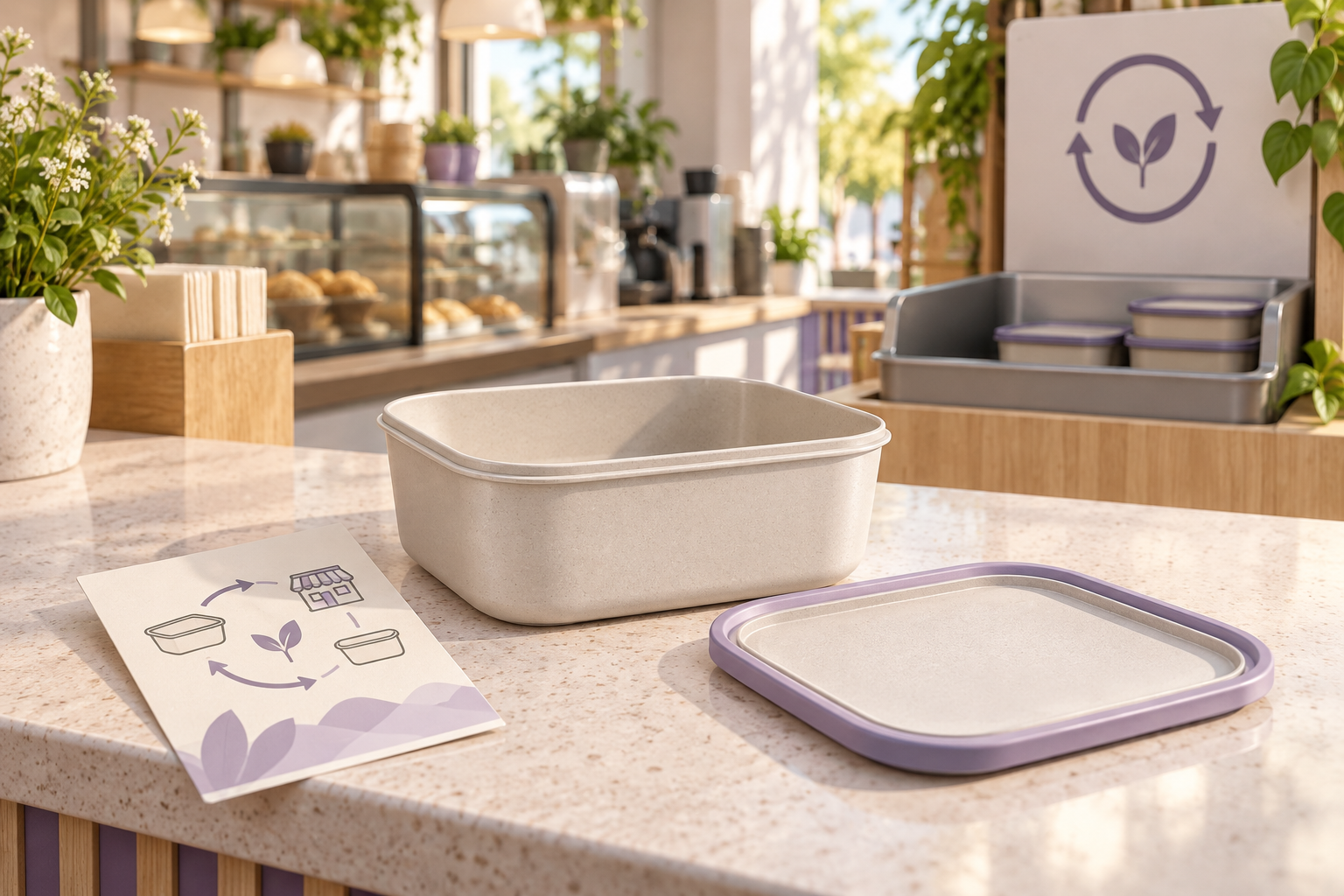
Многоразовый контейнер после доставки должен быстро ответить на три вопроса: нужно ли его возвращать, куда отнести и как связаться с кафе. Удобная инструкция видна до открытия упаковки, не теряется среди брендинга и остаётся понятной после еды. Ниже — способ собрать текст, расположить его на крышке или вкладыше и проверить макет в реальных условиях.
Сначала определите, что именно возвращает гость
Начните не с шрифта, а с предмета и сценария. У кафе может быть несколько видов тары: контейнер для горячего блюда, стакан, приборы или сумка. У каждого свой срок и маршрут возврата. Если написать только «верните упаковку», посетитель не поймёт, относится ли просьба к крышке, самому контейнеру или всему комплекту.
Составьте короткий перечень: какие предметы забирает гость, что из них возвращается и в каком состоянии. Обозначьте одно понятное название для каждого предмета и используйте его последовательно в сообщении, на заказе и у стойки. Если условия отличаются для разных позиций, не пытайтесь вместить несколько правил в одну универсальную фразу — сделайте отдельные наклейки или вкладыши.
Полезно заранее ответить на вопросы команды: принимают ли тару во всех точках или только в той, где выдали заказ; можно ли передать её курьеру при следующем заказе; куда положить грязный контейнер; как поступить, если точка закрыта. В печатной инструкции должны оказаться только варианты, которые заведение действительно готово выполнять. Не обещайте возврат через курьера или конкретный адрес, пока этот процесс не согласован внутри.
Постройте сообщение по порядку действий
Гость читает упаковку быстро: у двери, за столом или уже после еды. Поэтому инструкция должна работать как маршрут, а не как рекламный абзац. Сначала покажите действие, затем место, время или способ, а в конце — канал для вопроса. Если нужен депозит или другое условие, назовите его простыми словами и рядом объясните, где уточнить детали.
Для базовой карточки достаточно четырёх смысловых строк:
- Действие: «Верните контейнер» или «Контейнер можно вернуть».
- Место: точный адрес стойки, название точки или согласованный способ передачи.
- Срок или момент: только если он установлен и важен для работы сервиса.
- Контакт: короткий адрес страницы, телефон или QR-код с подписью о том, что откроется.
Используйте глагол, который описывает реальное действие. «Сдайте», «оставьте» и «принесите» звучат похоже, но задают разные ожидания: контейнер передают сотруднику, кладут в обозначенную зону или возвращают лично. Если тара принимается только чистой или пустой, сформулируйте это прямо и доброжелательно. Не прячьте такое условие в сноску.
Когда возврат добровольный, так и обозначьте его. Когда есть плата, залог или иной стимул, разделите шаг и условие: сначала что сделать, затем что произойдёт после. Избегайте формулировок «выгодно», «экологично» или «бесплатно», если рядом нет точного пояснения. Тон должен помогать гостю действовать, а не создавать ощущение упрёка.
Выберите поверхность: контейнер, крышка или вкладыш
Печатать всё на стенке контейнера удобно не всегда. Изогнутая поверхность деформирует строку, конденсат и жирные пальцы мешают чтению, а крышка может отделиться от основания. Сначала решите, в какой момент человек должен увидеть сообщение.
На крышке можно дать короткий первый сигнал: «Верните контейнер» и указатель на инструкцию. На боковой стенке — место возврата и контакт. Если поверхность мала, используйте отдельный вкладыш или бумажную ленту вокруг комплекта. Вкладыш позволяет разместить полную инструкцию, но его легко выбросить вместе с упаковкой; продублируйте ключевое действие на самом контейнере.
Проверьте весь цикл глазами пользователя. При вручении заказа видно ли, какая часть возвращается? После снятия крышки остаётся ли инструкция? Можно ли отличить крышку от контейнера, если предметы лежат отдельно? Если многоразовой является только основа, крупно назовите именно её, а не комплект целиком.
Макетируйте сообщение на физическом образце или на точном по размеру бумажном прототипе. Оберните его вокруг тары, закройте крышку, положите контейнер в пакет и достаньте снова. Так обнаруживаются места, где строка уходит на шов, сгиб, ручку или участок, закрываемый наклейкой заказа. На изогнутой стороне оставляйте текстовые строки короче и не ставьте важные слова у края.
Разведите инструкцию и бренд
Логотип, цвет и декоративная надпись помогают узнать кафе, но не должны конкурировать с маршрутом возврата. Отведите инструкционному блоку отдельную зону: спокойный фон, понятная метка, короткий заголовок. Название бренда можно оставить, однако сначала должно читаться действие.
Для основной фразы подойдёт прямой шрифт с различимыми кириллическими буквами и устойчивым рисунком в небольшом размере. Рукописное начертание можно использовать в короткой подписи или акценте, если его легко прочесть с первого взгляда. Не набирайте им длинный адрес, телефон или условия: похожие буквы и цифры затрудняют чтение, особенно на движущейся упаковке.
Короткий вывод
Инструкция на многоразовой таре работает, когда гость с первого взгляда понимает, какой предмет вернуть и куда его отнести. Сначала подтвердите маршрут с командой, затем разместите ключевой шаг на самом контейнере и проверьте его на образце в реальном сценарии доставки.